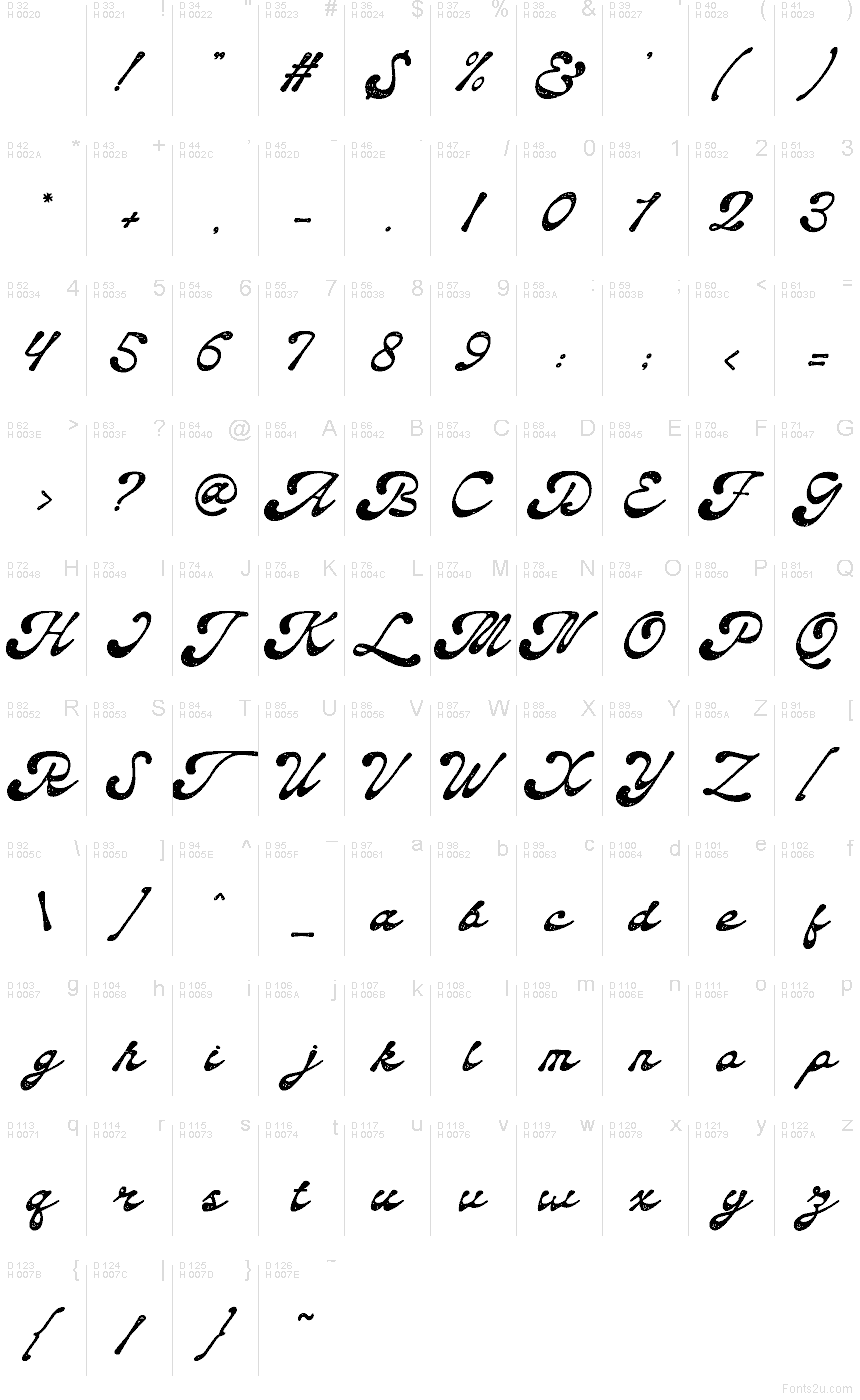
Daux Lavande Texture od Putracetol Studio je bezplatné texturované štětcové písmo s rozlehlými křivkami a lehkým pohybem ručně malovaného písma. Široké tahy přecházejí do jemných spojů a dlouhých kliček a rozptýlená opotřebovaná místa dodávají písmenům potištěný, zvětralý povrch. Pohyb působí rychle a sebejistě.
Obalový design je přirozeným prostředím pro jeho ručně vytvořený tvar, zejména na svíčkách, mýdlech a etiketách butikových potravin. Hodí se také na hudební plakáty a pozvánky na akce, které těží z expresivního písma. Plynulé písmo odkazuje na osobní podpisy a romantické tiskoviny.